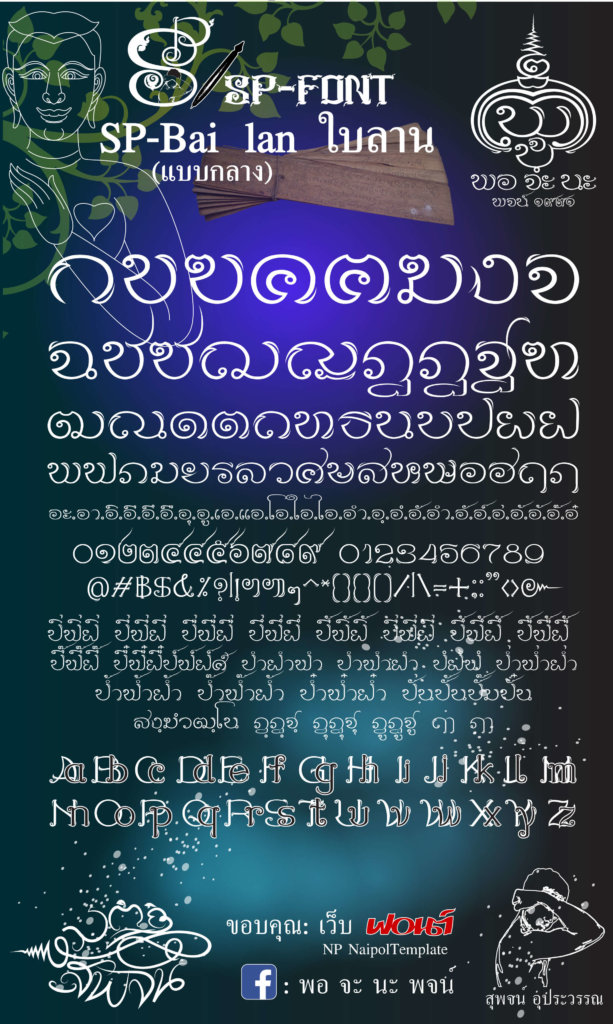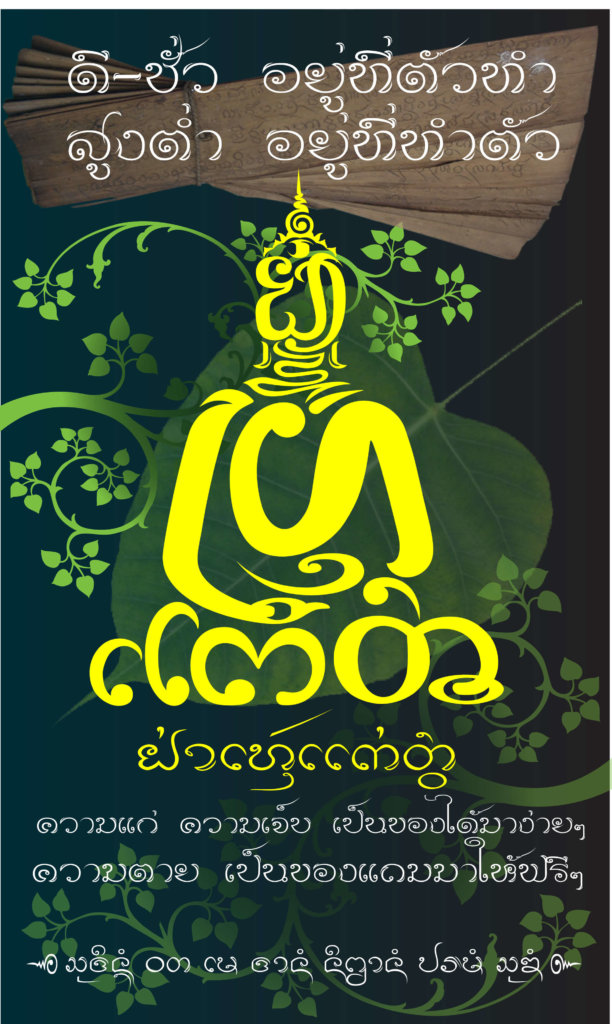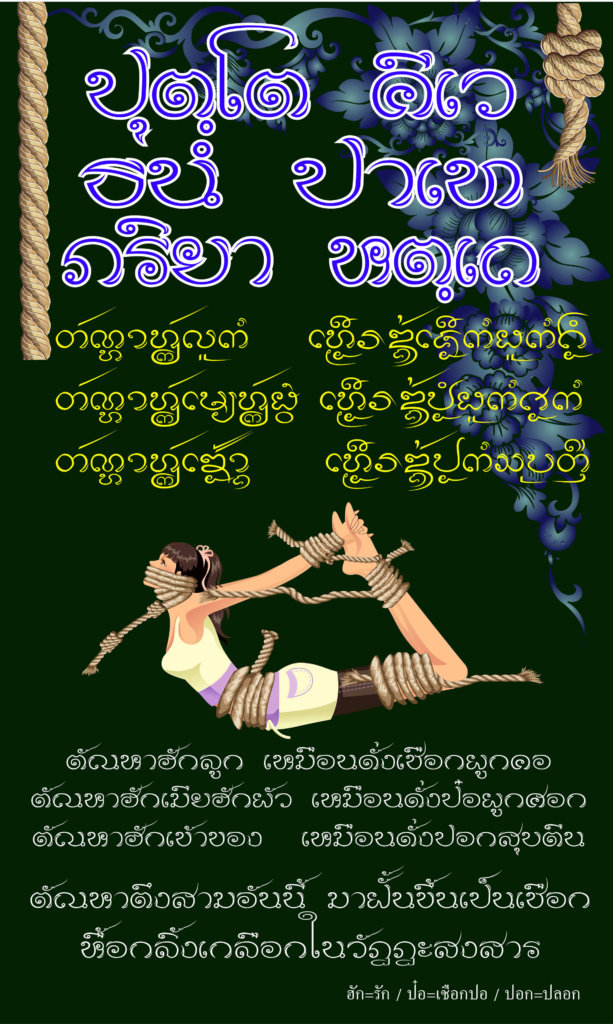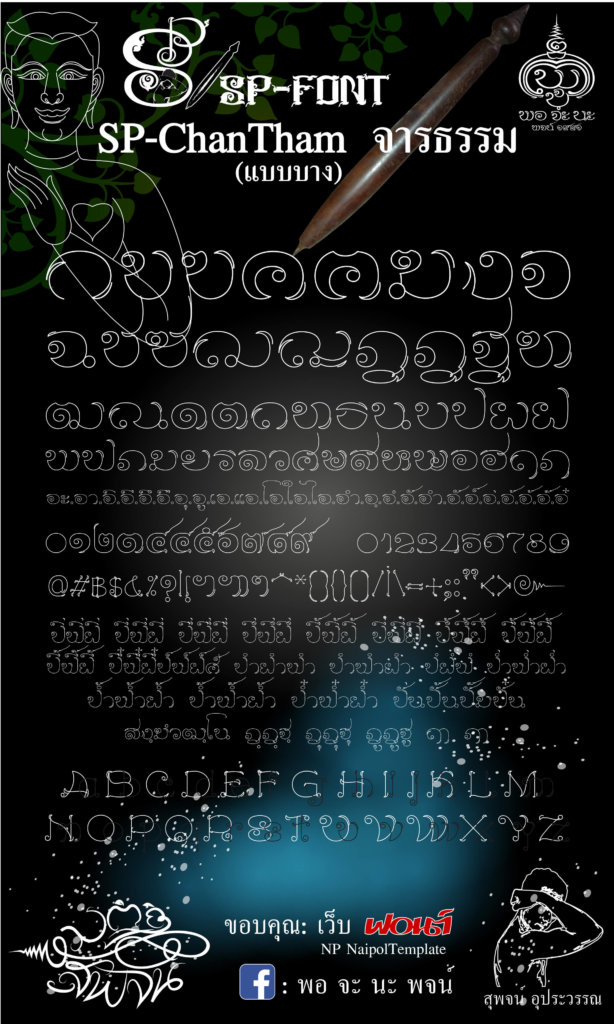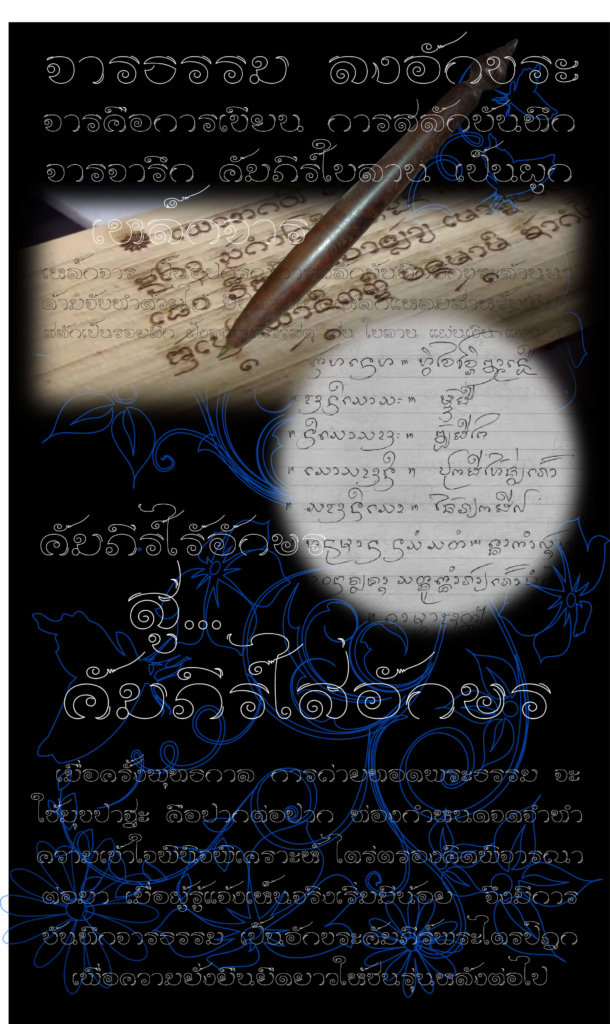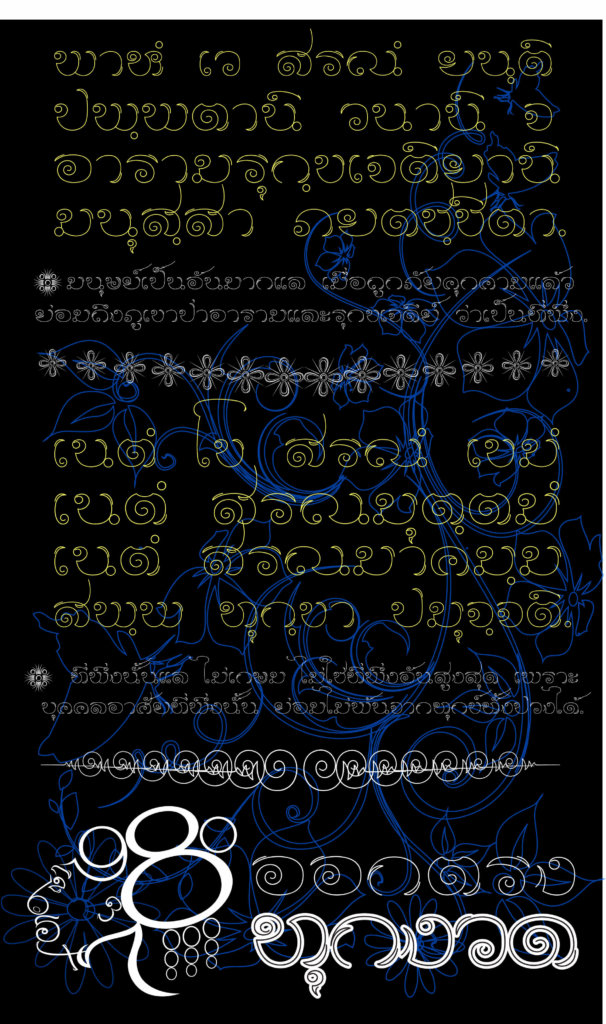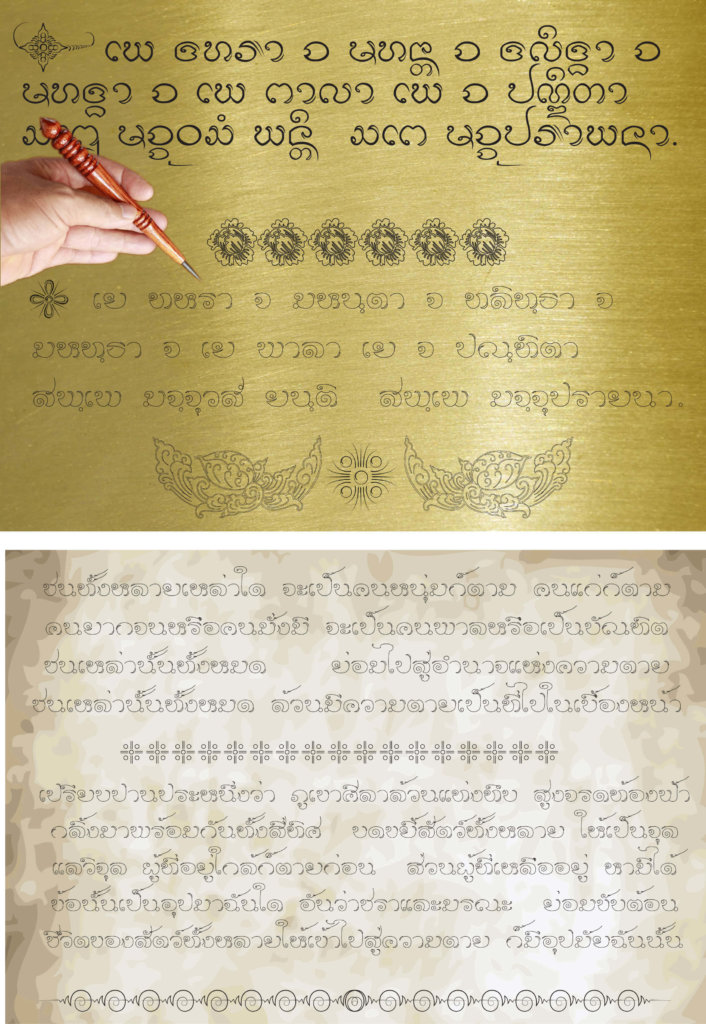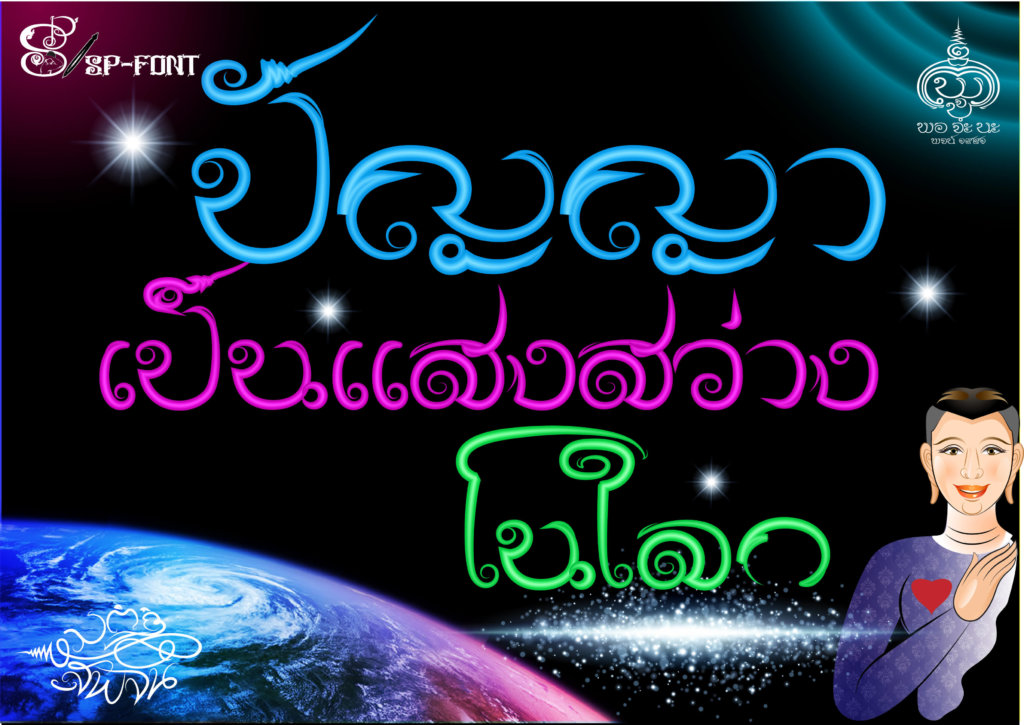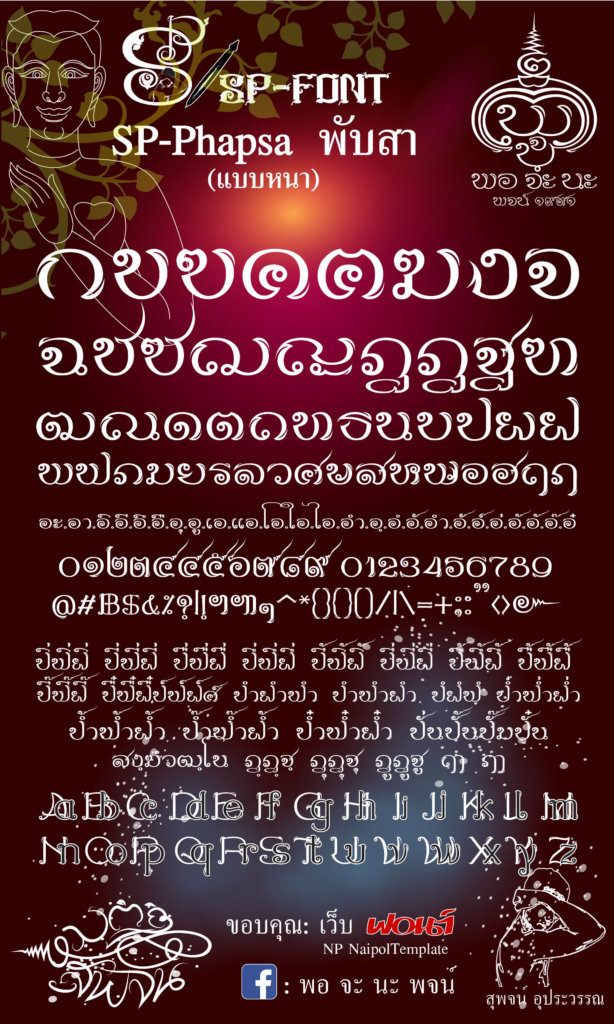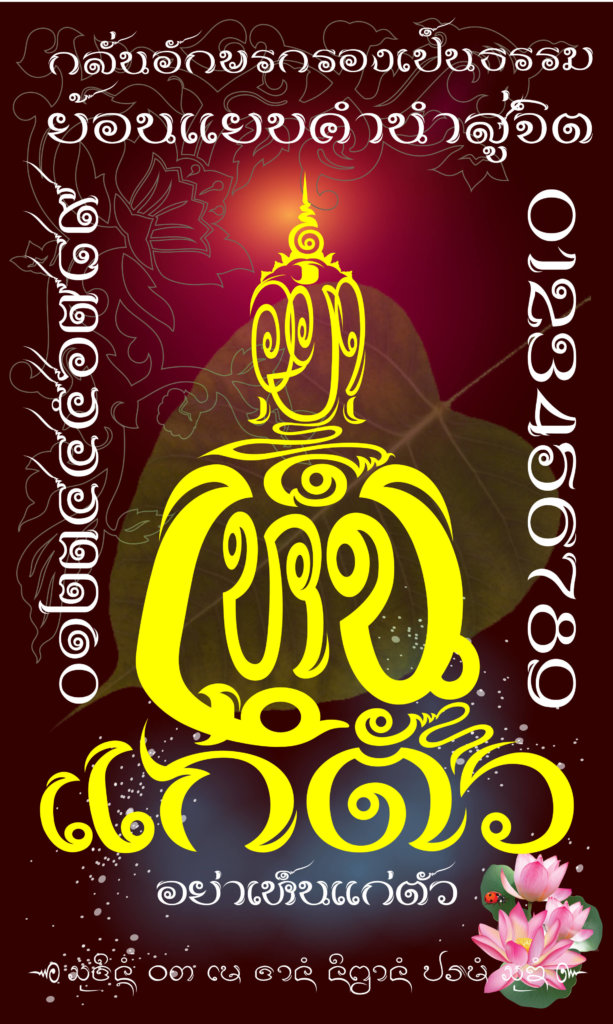
จารธรรม / ใบลาน / พับสา
ฟอนต์ SP-Chan Tham ( จารธรรม) / SP-Bai lan (ใบลาน) / SP-Phapsa (พับสา) ทั้ง 3 ชุดนี้ เป็นฟอนต์ไทยสไตล์ล้านนา ด้วยผู้ทำเป็นคนเกิดในพื้นที่ภาคเหนือ เลยอยากจะทำอักษรไทยที่มีอัตลักษณ์ทางล้านนา โดยโครงสร้างรูปแบบ ทำให้มีคุณลักษณะคล้ายกับตัวอักษรล้านนา ที่ลงอักขระด้วยเหล็กจาร  แล้วเพิ่มเป็นตัว กลางและหนา เพราะแบบบางอาจจะดูไม่ถนัดนัก หางวรรณยุกต์บนจะขีดตวัดขึ้นยาวๆ จึงมีการทับซ้อนกันบ้าง ตามอักขรวิธีในการเขียนอักษรล้านนา
SP-Chan Tham (จารธรรม)
SP-Bai lan (ใบลาน)
SP-Phapsa (พับสา)